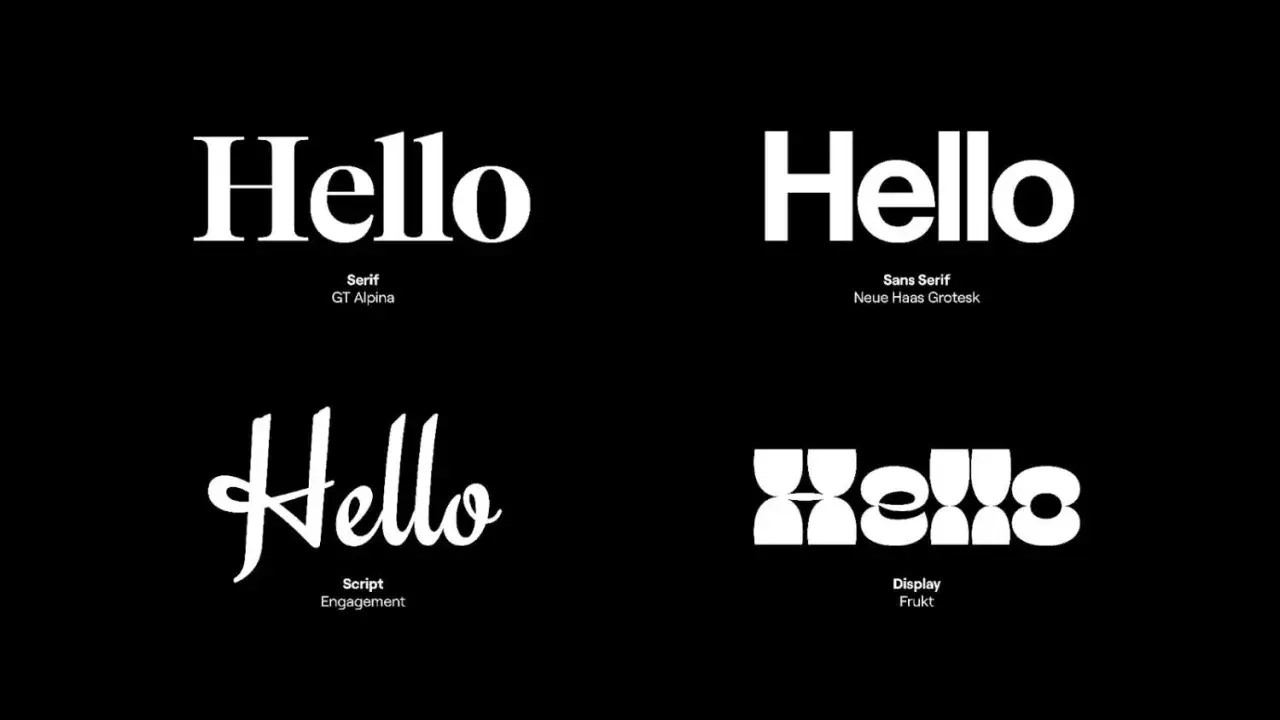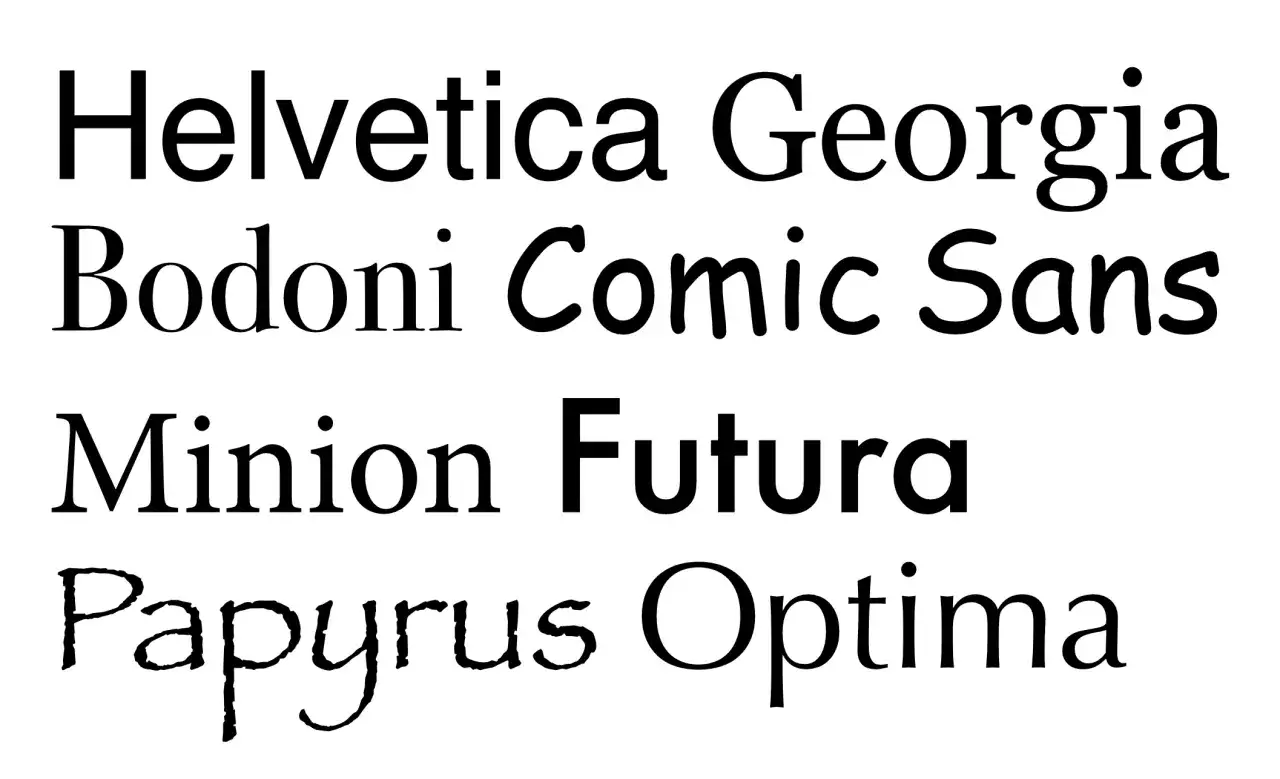
Czcionka do napisu - jak wybrać krój, który pasuje?
Cztery wersje napisu "Hello" w różnych stylach czcionki: szeryfowa, bezszeryfowa, skryptowa i wyświetlacza.
Ten sam tekst może wyglądać elegancko, nowocześnie albo zupełnie nieczytelnie, zależnie od wybranego kroju pisma. Dobór czcionki do napisu wpływa nie tylko na estetykę, lecz także na odbiór marki, plakatu, zaproszenia czy ilustracji. Pokażę, jak rozpoznać rodzaj pisma, dopasować go do zastosowania, zadbać o polskie znaki i uniknąć błędów, przez które nawet ciekawy projekt traci charakter.
Dobry napis łączy styl z czytelnością
• Zastosowanie decyduje o tym, czy lepszy będzie krój prosty, szeryfowy, odręczny czy dekoracyjny.
• Odstępy między literami często wpływają na wygląd mocniej niż sama nazwa fontu.
• Polskie znaki trzeba sprawdzić przed rozpoczęciem projektu, szczególnie przy ozdobnych krojach.
• Dwa kroje pisma zwykle wystarczą, aby stworzyć spójną i interesującą kompozycję.
• Generator czcionek przydaje się do inspiracji, ale nie zawsze tworzy prawdziwy font gotowy do druku.
Co właściwie oznacza czcionka do napisu
W codziennym języku „czcionka” oznacza wygląd liter, choć w typografii precyzyjniej mówi się o kroju pisma albo foncie. Krój określa kształt znaków, ich proporcje, grubość, kontrast oraz sposób łączenia się liter. To właśnie te cechy sprawiają, że napis wygląda jak fragment gazety, podpis artysty albo logotyp technologicznej firmy.
Sam tekst jest dopiero materiałem. O jego charakterze decydują również rozmiar, interlinia, kerning i kolor. Kerning oznacza ręczne dopasowanie odstępów między konkretnymi parami liter, na przykład „A” i „V”. W krótkim napisie ma ogromne znaczenie, bo jedna zbyt duża przerwa potrafi zepsuć nawet bardzo dobry projekt.
Trzeba też odróżnić font od gotowego napisu jako grafiki. Font pozwala wpisywać i edytować tekst, natomiast napis zapisany jako obraz, na przykład w formacie SVG lub PNG, może zostać dowolnie przekształcony bez konieczności instalowania kroju. To ważne przy logo, nadruku i ilustracji, ale mniej wygodne, gdy tekst ma być później zmieniany.
Rodzaje krojów i ich charakter
Nie wybieram kroju dlatego, że „ładnie wygląda” w katalogu. Zawsze sprawdzam, jakie emocje wywołuje i czy pasuje do materiału, na którym pojawi się napis. Inaczej projektuje się nazwę pracowni ceramicznej, inaczej tytuł plakatu koncertowego, a jeszcze inaczej napis na szyldzie.
Rodzaj kroju Jak wygląda Najlepsze zastosowanie Na co uważać
Bezszeryfowy Proste zakończenia, czysta forma Logo, plakat, strona internetowa, nowoczesna marka Zbyt neutralny krój może wyglądać bezosobowo
Szeryfowy Małe zakończenia przy końcach liter Zaproszenia, publikacje, projekty inspirowane historią Delikatne szeryfy mogą zniknąć w małym rozmiarze
Odręczny Nawiązuje do pisma ręcznego Rękodzieło, kartki, ilustracje, projekty osobiste Litery często są trudne do odczytania
Skryptowy Litery przypominają kaligrafię lub pismo połączone Śluby, kosmetyka, moda, eleganckie opakowania Nie sprawdza się w długich tekstach i wersalikach
Dekoracyjny Ma wyraziste, nietypowe kształty Plakaty, okładki, tytuły, projekty artystyczne Użyty w nadmiarze szybko męczy wzrok
Najbardziej uniwersalne są kroje bezszeryfowe, takie jak Montserrat, Poppins czy Lato, ponieważ zachowują czytelność w wielu rozmiarach. Nie oznacza to jednak, że zawsze są najlepsze. Do projektu o historycznym lub rzemieślniczym charakterze krój szeryfowy może wnieść więcej wiarygodności niż kolejny geometryczny font.
W przypadku ozdobnego napisu traktuję dekoracyjność jak przyprawę. Jedno wyraziste słowo może dzięki niej zyskać energię, ale cały akapit zapisany takim fontem zwykle staje się trudny do rozszyfrowania. Im krótszy napis, tym więcej swobody, ponieważ odbiorca ma mniej znaków do odczytania.
Różne rodzaje czcionek: Helvetica, Georgia, Bodoni, Comic Sans, Minion, Futura, Papyrus, Optima.
Jak dobrać styl do konkretnego zastosowania
Logo i nazwa marki
W logo liczy się rozpoznawalność oraz możliwość użycia napisu w różnych rozmiarach. Najlepiej zaczynać od prostego kroju i dopiero później dodawać charakter przez modyfikację jednej litery, nietypowe zakończenie albo indywidualny kerning. Logo powinno działać zarówno na ekranie telefonu, jak i na dużym szyldzie.
Do marki technologicznej pasują często formy geometryczne i bezszeryfowe. Pracownia artystyczna może pozwolić sobie na krój odręczny, ale trzeba go przetestować w małej wersji. Jeśli nazwa traci czytelność po zmniejszeniu do około 120-160 pikseli szerokości, prawdopodobnie wymaga uproszczenia.
Plakat i okładka
Plakat pozwala na większy kontrast. Tytuł może być bardzo duży, ciężki lub nietypowy, a informacje dodatkowe powinny pozostać spokojniejsze. Dobrym rozwiązaniem jest połączenie jednego kroju dekoracyjnego z jednym prostym, zamiast używania czterech różnych fontów.
Przy tytule plakatu często sprawdza się rozmiar od 48 do 120 px w projekcie cyfrowym, zależnie od formatu i odległości oglądania. To nie jest sztywna norma, lecz praktyczny punkt wyjścia. Ostatecznie ważniejsze od liczby jest to, czy napis zachowuje rytm i kontrast z tłem.